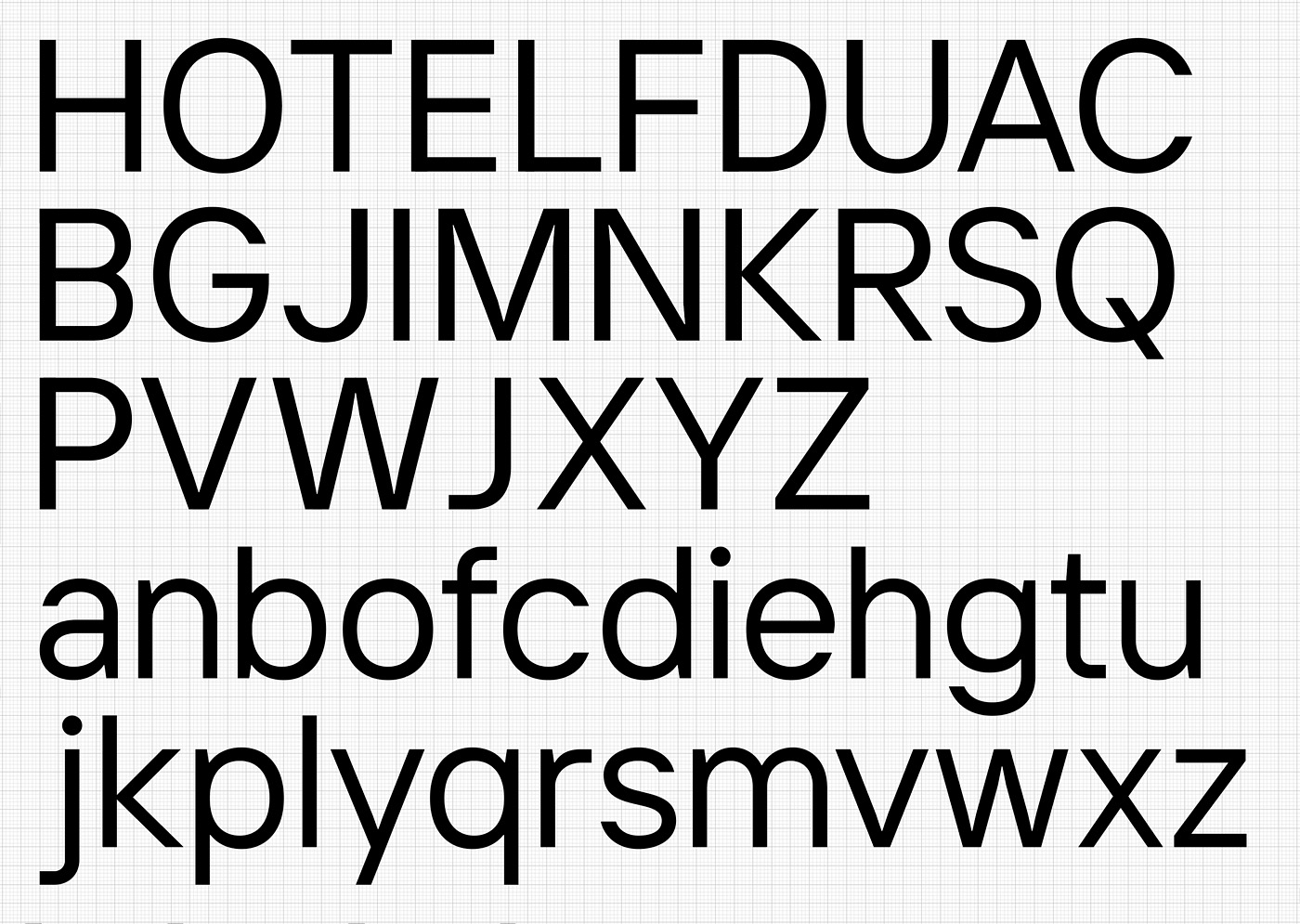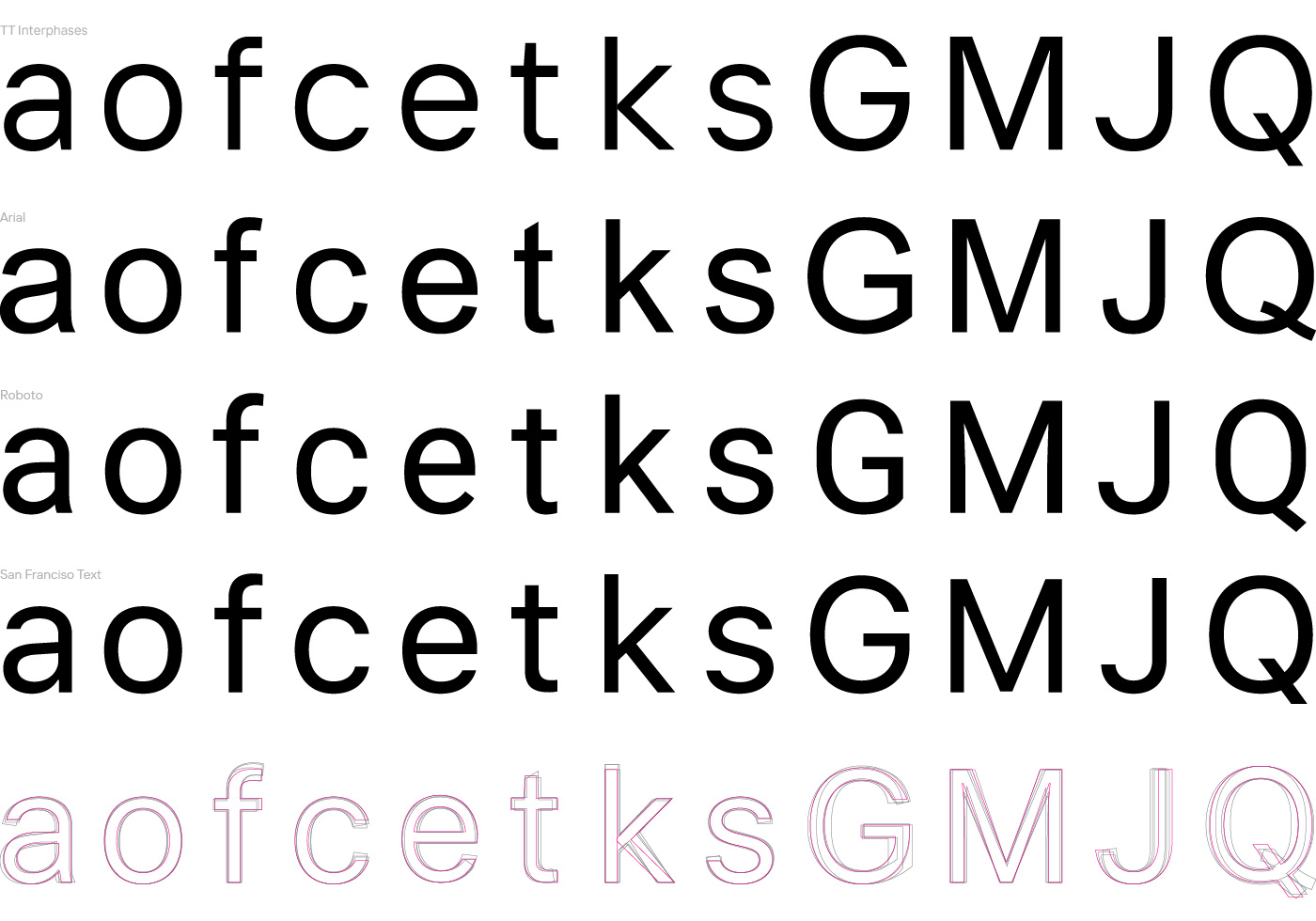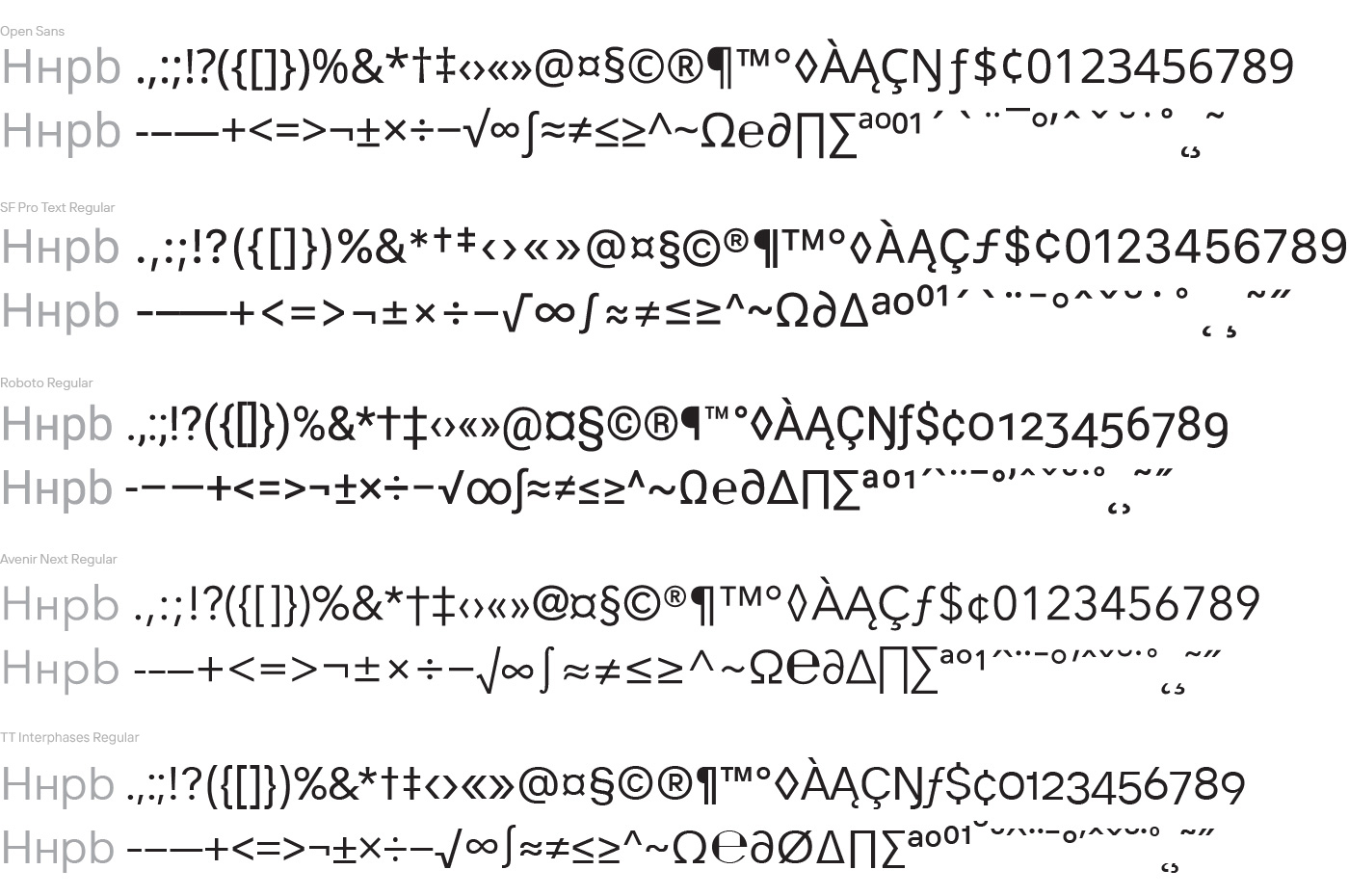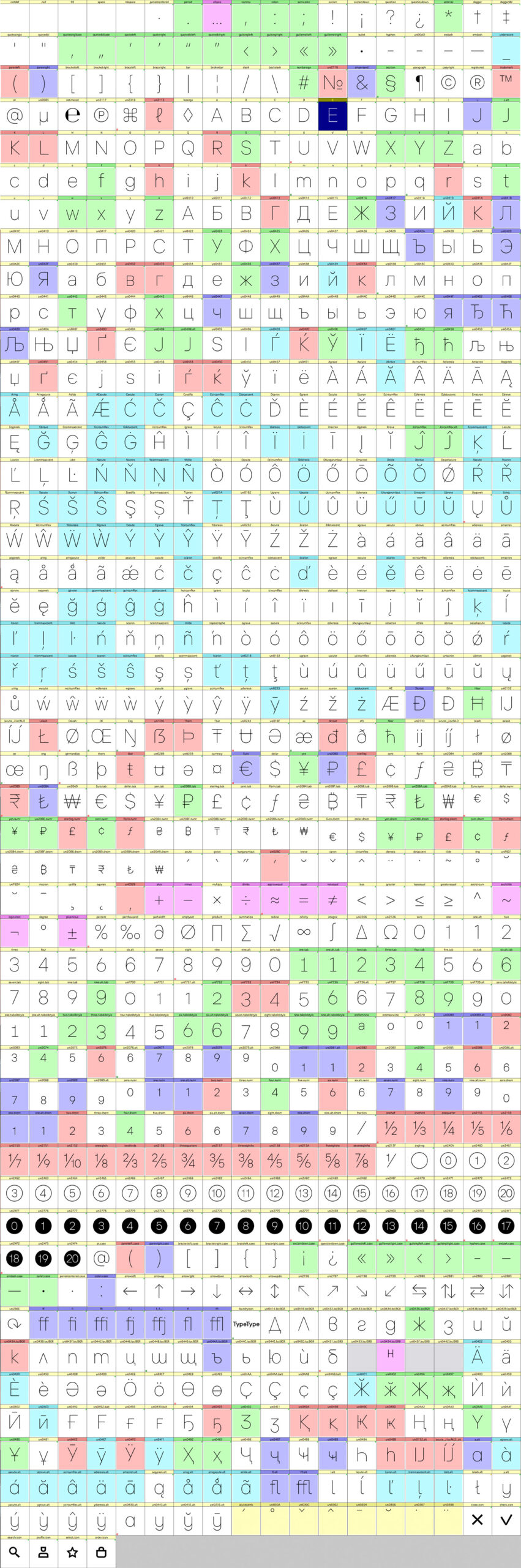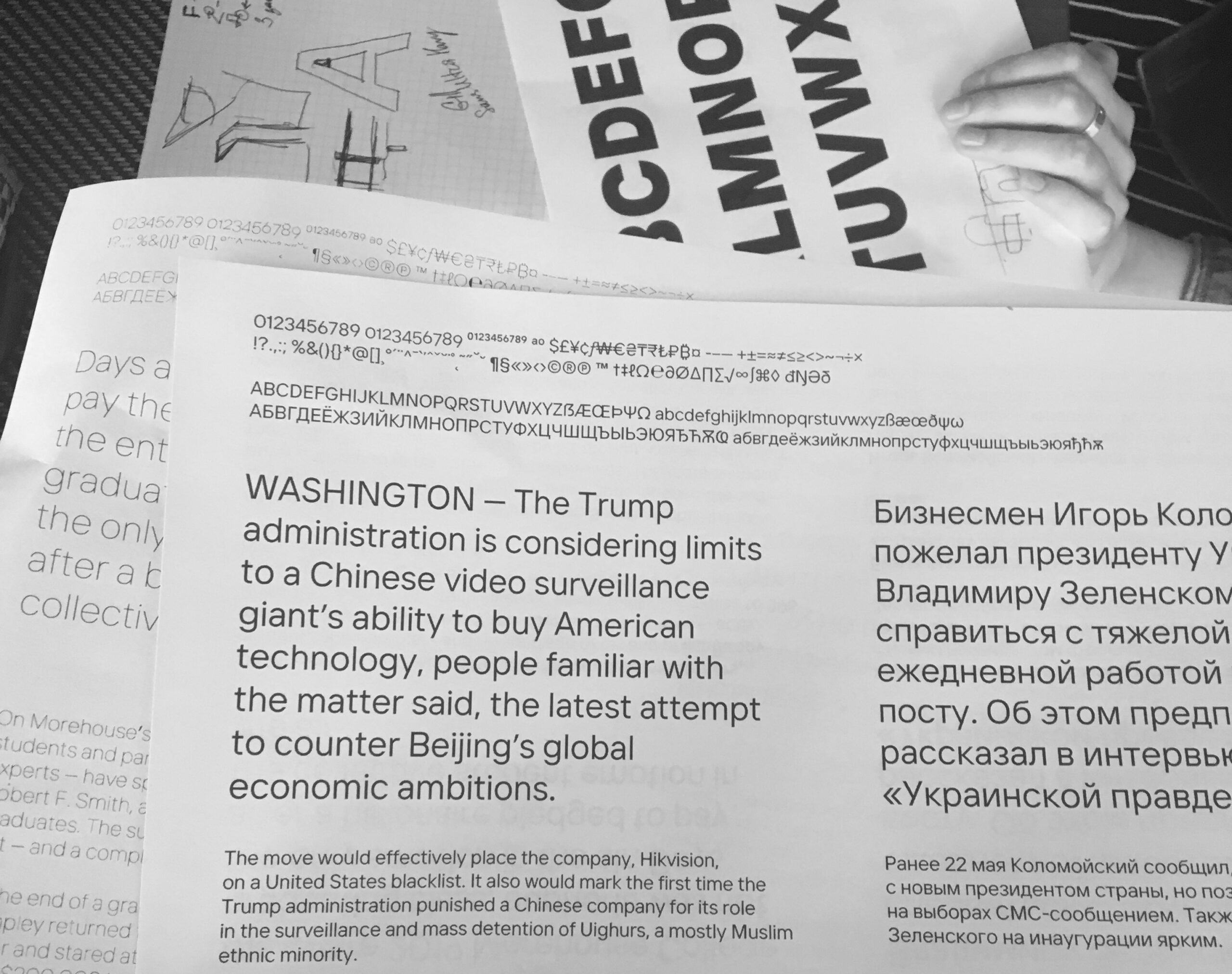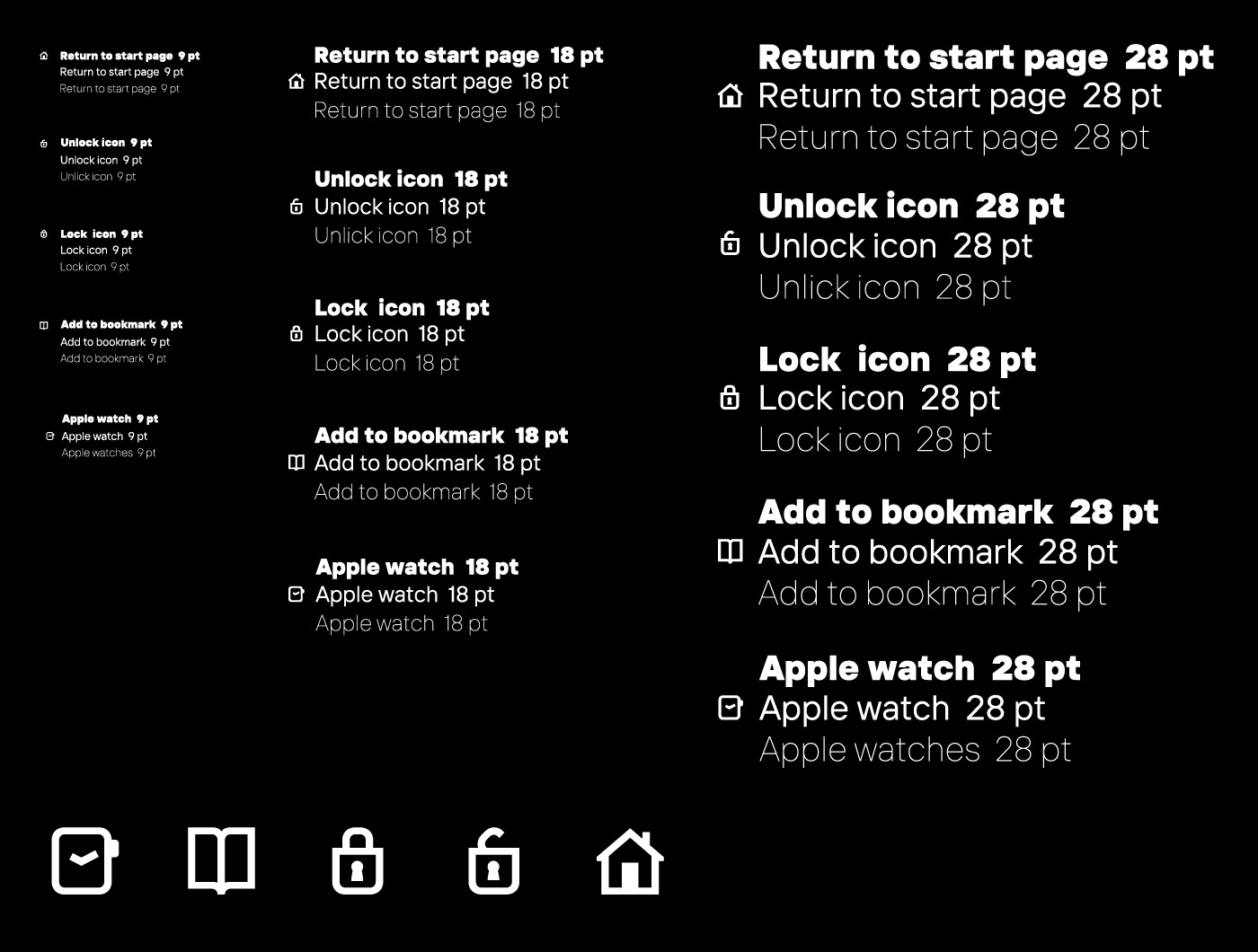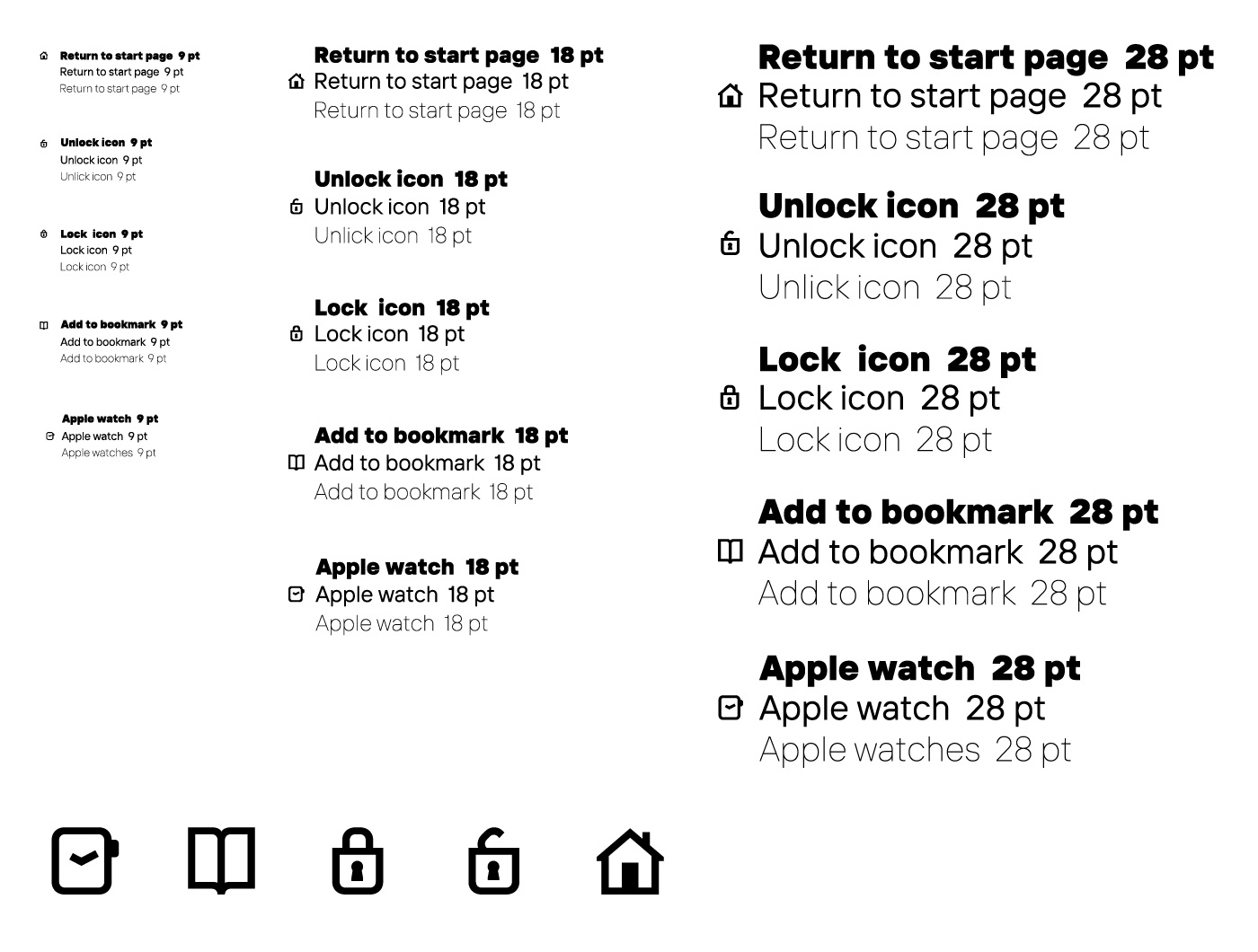
История создания интерфейсной шрифтовой гарнитуры TT Interphases
Вступление
Весной 2018 года, основываясь на опыте таких шрифтов как TT Commons и TT Norms, мы внутри TypeType сформулировали для себя идею универсального и полезного шрифта, который будет использоваться в современных интерфейсах на большинстве известных мобильных и веб-платформах.
У него должны быть лучшие пропорции в категории, а также широкая палитра начертаний, знаков и OpenType фич. Шрифт должен хорошо «вставать» в верстку при замене старого интерфейсного шрифта на наш новый шрифт. Количество начертаний, которое должно было быть в данном семействе, мы определили как «оптимально максимальное». Отдельно для программистов мы решили сделать моноширинную версию гарнитуры из 4 начертаний (так называемой «золотой четверки»), которая основана на рисунке оригинальной гарнитуры. Хорошо, когда есть такая консонансная пара гарнитур.
Данный шрифт должен стать универсальным и удобным инструментом для дизайнеров, которые активно используют интерфейсные шрифты в своих проектах. Ну и не будем забывать о творческой составляющей проекта — шрифт должен быть красивым, элегантным, в тоже время невидимым и нейтральным. Технически данный шрифт должен быть идеальным: иметь современный хинтинг, а также вариативную версию для тех, кто в теме. Так началась история проекта, который продлился более одного календарного года.
Этап 1 — Исследование
Мы подошли к процессу основательно. Были рассмотрены все самые популярные шрифтовые гарнитуры, которые принято использовать в интерфейсах, они все были классифицированы, разбиты по группам и проанализированы.
Таблица с анализом существующих интерфейсных шрифтов
Таблица с анализом существующих интерфейсных шрифтов
Итогом этих сводных данных стала большая презентация, в рамках которой мы попытались проанализировать и выявить основные особенности в построении знаков, такие как:
• степень закрытости/открытости апертуры «а», «с», «е» знаков;
• степень округлости/сквадраченности окружностей в круглых знаках;
• формы точек и запятых, а также других подобных элементов;
• условно открытые и условное закрытые формы некоторых цифр, таких как 4, 6, 9.
На общей встрече мы дискутировали и определились с направлением дальнейшей работы.
Первая внутренняя презентация будущего проекта
Мы не могли не учитывать уже созданные и активно используемые шрифты, поэтому мы посчитали пропорции всех популярных шрифтов из данной тематики и через этот анализ пришли к собственным выводам и пропорциям. Теперь мы можем не опасаться, что при замене шрифта в уже сверстанных макетах у дизайнера интерфейсов «поедет верстка на двухстах отрисованных экранах», а также резко изменится степень черноты набора текста аналогичного начертания, ведь благодаря детально проведенному анализу «весовые начертания» будут близки относительно конкурентов.
Мы измеряли в условных шрифтовых единицах такие параметры, как x-height, для прописных знаков H-weight, толщина H-stem, толщина H-crossbar, а также аналогичные параметры для строчных знаков. В результате оказалось, что большинство шрифтов сильно похожи друг на друга, а некоторые и вовсе идентичны по многим параметрам.
Также нами были измерены различия между величинами вертикальных штрихов разных начертании в рамках одной гарнитуры, они также оказались близки друг к другу и в основном выполнены по формуле Пабло Импаллари, в рамках которой прирост черного в начертаниях осуществляется максимально гармонично (в светлых начертаниях прирост черного осуществляется быстро, в жирных начертаниях прирост черного осуществляется медленно).
Таблица с основными метриками интерфейсных шрифтов
Таблица с основными метриками интерфейсных шрифтов
Не забываем и про наших любимых клиентов, коллег и друзей. Решаем провести количественное маркетинговое исследование. Для этого мы сформировали онлайн-опросник по поводу интерфейсных шрифтов, которыми пользуются наши большие ИТ-гиганты, а также ведущие диджитал агентства страны. В результате мы получили более 50 ответов с детальной информацией, что натолкнуло нас на дополнительные размышления относительно кассового состава и нюансах характера создаваемой нами шрифтовой гарнитуры.
Результаты количественного маркетингового исследования
Этап 2 — Отрисовка базового начертания
После утверждения всех базовых пропорций шрифта, а также уточнения всех нюансов, относящихся к формам знаков шрифта, мы приступили к отрисовке основных знаков регулярного начертания, чтобы проверить наши гипотезы. Первый подход шрифту сделан в сетке 5×5 шрифтовых единиц. В первое начертание были заложены все стилеобразующие элементы шрифта.
Основные знаки начертания Regular
В ходе коллективного обсуждения проекта была выдвинута гипотеза о том, что формы окружностей получились слишком простыми и для того, чтобы их разнообразить было предпринято две попытки их видоизменить. Первая попытка — сделать их более cквадраченными, вторая — добавить прямые отрезки на вертикальных штрихах и посмотреть на результат.